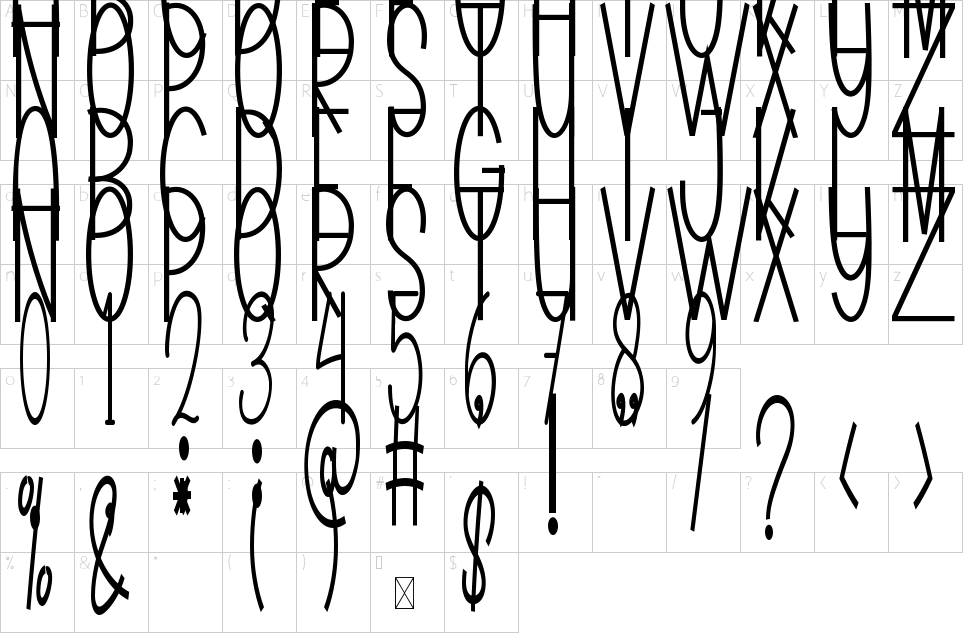
Descubra a beleza única e delicada do December Handmade Font para suas criações digitais! Esta fonte é perfeita para adicionar um toque artesanal aos seus projetos, seja para nomes de eventos, desenhos animados ou até mesmo logotipos. Designada por InermediaSTUDIO, esta font foi projetada cuidadosamente para manter os detalhes finos e delicados que tornam o handmade tão único. Para quem aprecia uma fonte com um ar autêntico e artesanal, December Handmade é a escolha perfeita. Ideal tanto para usuários de Windows quanto Mac, esta fonte pode ser instalada em seu sistema operacional sem problemas. É uma opção gratuita que você não encontrará por outros lugares, tornando-o ainda mais especial. Seja qual for o projeto que está desenvolvendo, a December Handmade Font certamente traz um toque personalizado e artesanal ao seu trabalho. Seja para projetos profissionais ou de hobby, esta font é uma escolha ótima para quem valoriza a arte manual em seus recursos digitais. Descubra por si mesmo o poder desta fonte handmade e veja como ela pode transformar suas criações digitais!